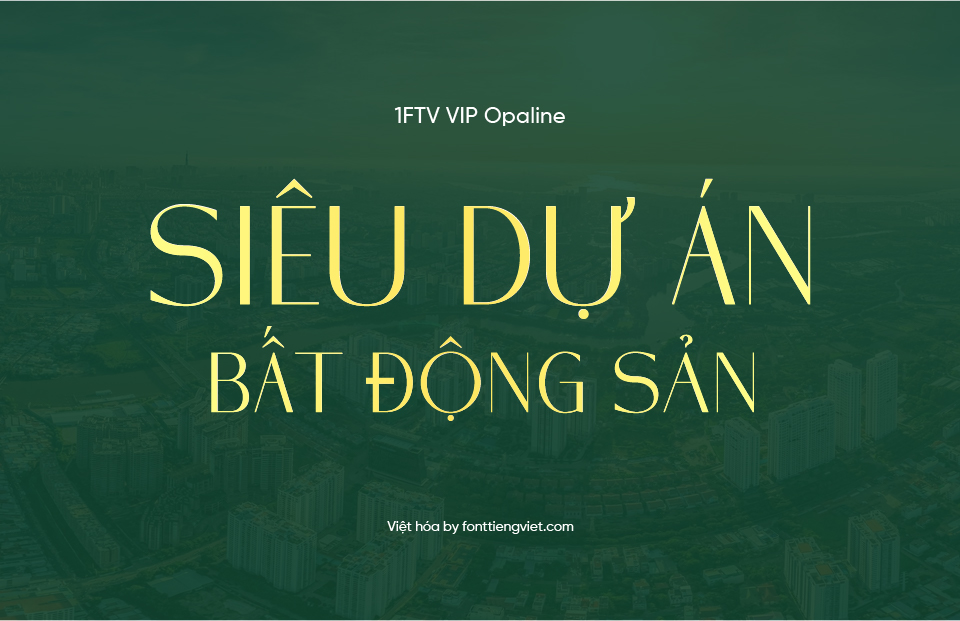
Tải Ngay Font việt hóa 1FTV VIP Opaline – Sự Kết Hợp Hoàn Hảo Giữa Sang Trọng Và Hiện ĐạiGiới thiệu về bộ Font việt hóa 1FTV VIP OpalineTrong thế giới thiết kế đồ họa hiện nay, việc lựa chọn một bộ Font Miễn Phí chất lượng đóng vai trò then chốt để tạo nên sự khác biệt cho tác phẩm. Một trong những cái tên đang thu hút sự chú ý của cộng đồng thiết kế chính là Font việt hóa 1FTV VIP Opaline. Đây là một bộ phông chữ thuộc phong cách Serif đương đại, mang trong mình vẻ đẹp thanh lịch nhưng không kém phần mạnh mẽ. Với các đường nét được trau chuốt tỉ mỉ, Opaline không chỉ là một công cụ truyền tải văn bản đơn thuần mà còn là một tác phẩm nghệ thuật giúp nâng tầm giá trị cho mọi dự án truyền thông và giáo dục.Đặc điểm thiết kế nổi bật của 1FTV VIP OpalineBộ Font việt hóa 1FTV VIP Opaline sở hữu cấu trúc chữ cân đối với các chân chữ mảnh và dứt khoát. Độ tương phản giữa nét thanh và nét đậm được tính toán kỹ lưỡng, tạo nên cảm giác dễ chịu cho mắt người đọc ngay cả khi sử dụng trong các đoạn văn bản dài. Đặc biệt, phiên bản việt hóa này đã được tối ưu hóa hoàn toàn hệ thống dấu tiếng Việt, đảm bảo không xảy ra lỗi hiển thị hay mất nét thường gặp ở các bộ font ngoại nhập. Điều này giúp các thầy cô giáo và học sinh có thể dễ dàng ứng dụng vào việc thiết kế bài giảng, làm báo cáo hay trình bày các tài liệu học tập một cách chuyên nghiệp nhất.Tại sao bạn nên chọn Font việt hóa 1FTV VIP Opaline cho dự án của mình?Lý do đầu tiên khiến Font việt hóa 1FTV VIP Opaline trở nên phổ biến chính là tính đa dụng vượt trội. Dù bạn đang thiết kế bìa sách, poster sự kiện hay tiêu đề cho một trang web, bộ font này đều có khả năng thích nghi tuyệt vời. Nó mang lại cảm giác tin cậy và trang trọng, rất phù hợp với môi trường giáo dục đòi hỏi sự chỉn chu. Bên cạnh đó, các ký tự thay thế (alternates) và các tính năng OpenType tích hợp sẵn cho phép người dùng sáng tạo thêm nhiều biến thể độc đáo, giúp mỗi trang thiết kế trở nên sống động và có chiều sâu hơn.Ứng dụng thực tế trong thiết kế và học tậpHọc sinh và sinh viên có thể sử dụng Font việt hóa 1FTV VIP Opaline để trang trí cho các bài thuyết trình PowerPoint, làm cho nội dung trở nên thu hút và dễ theo dõi hơn. Trong khi đó, các nhà thiết kế chuyên nghiệp thường ưu tiên bộ font này cho các bộ nhận diện thương hiệu cao cấp hoặc thiệp mời sự kiện quan trọng. Nhờ khả năng hiển thị sắc nét trên cả màn hình kỹ thuật số và bản in, Opaline giúp duy trì sự thống nhất về mặt thẩm mỹ cho toàn bộ hệ thống tài liệu. Việc sử dụng một bộ font có bản quyền việt hóa tốt như 1FTV VIP Opaline cũng thể hiện sự tôn trọng đối với tác giả và tính chuyên nghiệp trong công việc.Hướng dẫn cài đặt và sử dụng Font việt hóa 1FTV VIP Opaline hiệu quảĐể tận dụng tối đa sức mạnh của Font việt hóa 1FTV VIP Opaline, bạn cần lưu ý đến cách phối hợp màu sắc và khoảng cách giữa các chữ cái (kerning). Một mẹo nhỏ là hãy kết hợp Opaline với một font không chân (Sans-serif) đơn giản cho phần nội dung chi tiết để tạo ra sự tương phản thị giác thú vị. Việc cài đặt cũng rất đơn giản, bạn chỉ cần tải tệp định dạng .otf hoặc .ttf về máy tính, chuột phải và chọn Install. Sau đó, font chữ sẽ tự động xuất hiện trong các phần mềm phổ biến như Microsoft Word, Photoshop hay Canva để bạn sẵn sàng bắt tay vào sáng tạo ngay lập tức.Kết luận và tải về bộ font chất lượngTóm lại, việc sở hữu một bộ phông chữ đẹp và chuẩn phong thủy như Font việt hóa 1FTV VIP Opaline sẽ giúp bạn tự tin hơn trong việc trình bày ý tưởng. Với sự hỗ trợ tận tình từ cộng đồng thiết kế tại Việt Nam, bạn hoàn toàn có thể tìm thấy những tài nguyên giá trị tại Font Miễn Phí, Font Việt Hóa, Font việt hóa 1FTV VIP Opaline để phục vụ cho mục đích học tập và làm việc phi lợi nhuận. Đừng ngần ngại thay đổi diện mạo cho các thiết kế của mình bằng bộ font đẳng cấp này ngay hôm nay để trải nghiệm sự khác biệt rõ rệt trong từng con chữ và từng trang giấy.
Font việt hóa 1FTV VIP Opaline